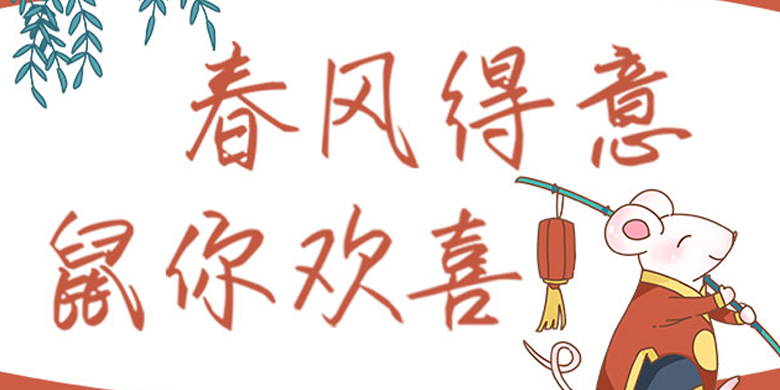
方正手迹-春风得意鼠你欢喜
方正手迹-春风得意鼠你欢喜,这款字体结构工整、笔画清晰,兼顾美观与易读性,适用于标题、正文、海报、包装、LOGO 等多种场景。字形优雅稳定,风格百搭耐看,适配日常排版与创意设计,让文字呈现更舒适、更具质感。方正手迹-春风得意鼠你欢喜一笔一画,皆是细节,以均衡的比例、流畅的线条打造舒适视觉体验,字形端正大气,风格简约现代。无论是商业设计、品牌宣传还是日常排版,都能轻松驾驭,让文字更有格调与力量。方正手迹-春风得意鼠你欢喜字体下载。
字体品牌: 方正手迹 设计师:余丹 字体分类:创意书写 字体属性:精品字 字符集:大陆简体(GB2312-80) 发布时间: 2020
春风得意鼠你欢喜这款字体笔势连贯,气韵悠长,作者多用提按,透出深厚的传统书法功底,让人百看不厌,赏心悦目。适用于现代诗歌、短文的排版,以及文化、品牌广告和产品包装设计,社交网络的个性化用字。